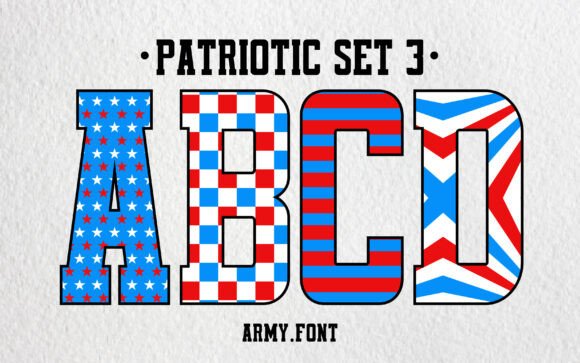
Patriotic Set 3
適切なデザイン要素を見つけるのは難しい場合がありますが、Patriotic Set 3は作品を即座に引き立てる優れたコレクションを提供します。
POD(オンデマンド印刷)製品、結婚式の招待状、またはソーシャルメディアのグラフィックを作成している場合でも、Patriotic Set 3は理想的です。